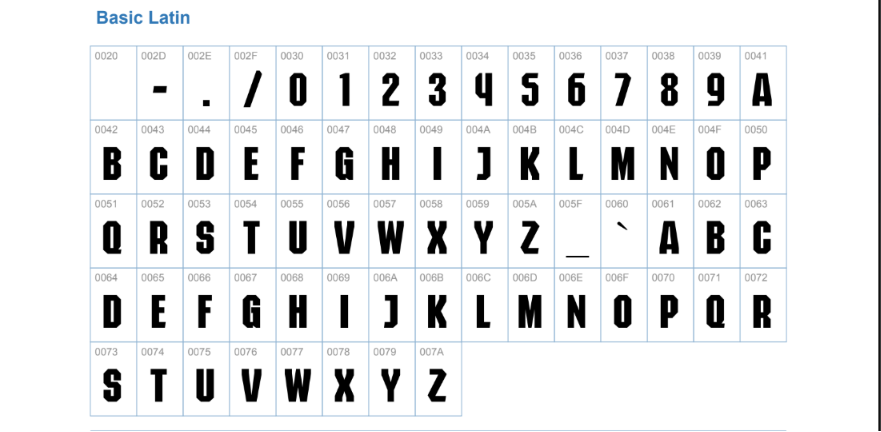
Chegou a hora de mostrar as caras. O Arsenal apresentou sua identidade visual completa para a temporada 2026-2027, e a nova tipografia promete dar um tempero especial aos uniformes.
Fãs e designers já estão de olho nos detalhes. A fonte oficial do clube londrino é um dos grandes trunfos do redesign, pensada para conectar tradição e modernidade. E o melhor: já está disponível para download.
Estilo visual da tipografia
A fonte aposta em números encorpados e traços retos, quase geométricos. O “7” aparece com o corte horizontal clássico do clube, enquanto o “2” ganha uma curva suave e agressiva ao mesmo tempo.
A legibilidade é o ponto alto. Mesmo nas transmissões em 4K ou nos letreiros do Emirates Stadium, cada caractere aparece nítido. Moderna, sim. Mas com a alma dos velhos tempos.
Aplicação no uniforme
- Home (titular): Nomes em branco sobre vermelho, com leve sombreado para destacar nas costas.
- Away (reserva): Fonte em azul-marinho ou dourado, dependendo da combinação de mangas.
- Third (terceiro): Traços mais finos e contorno verde-limão para contraste total.